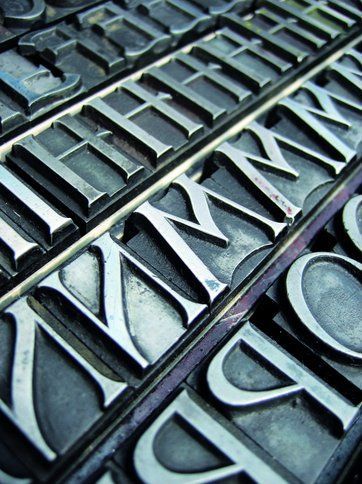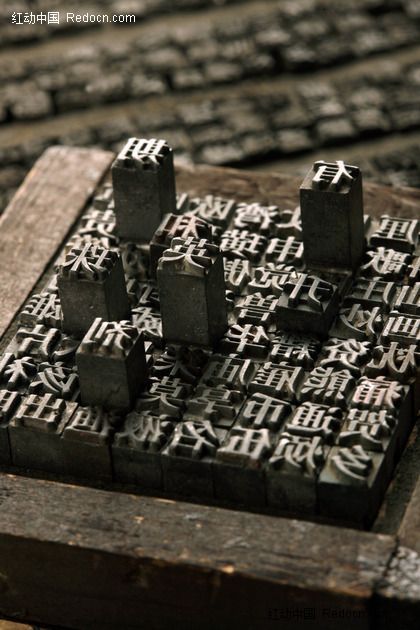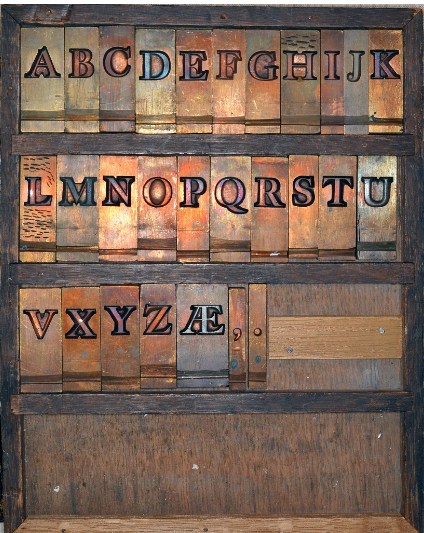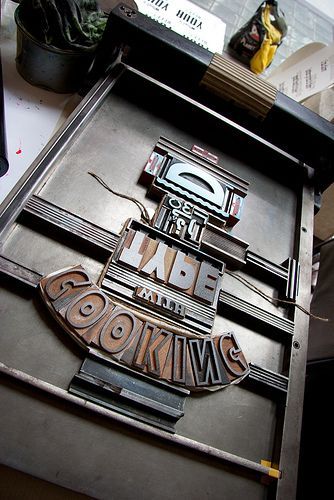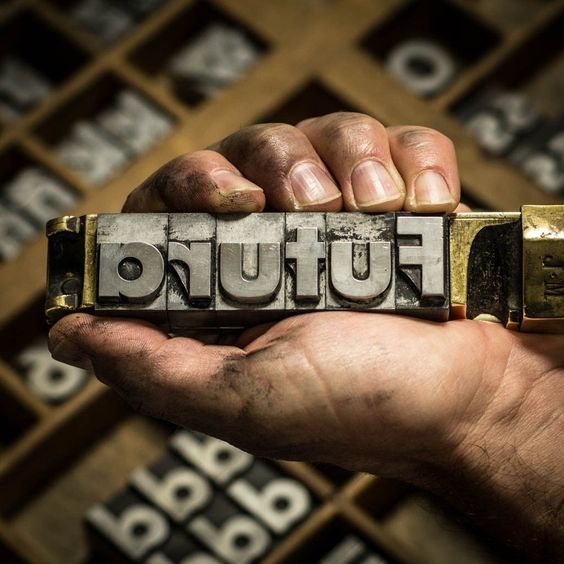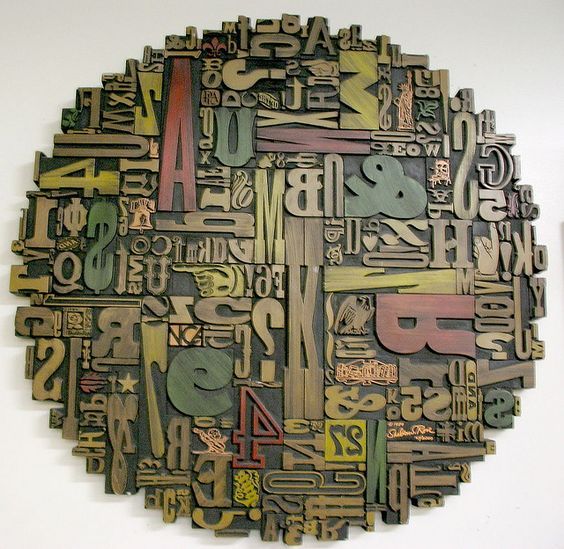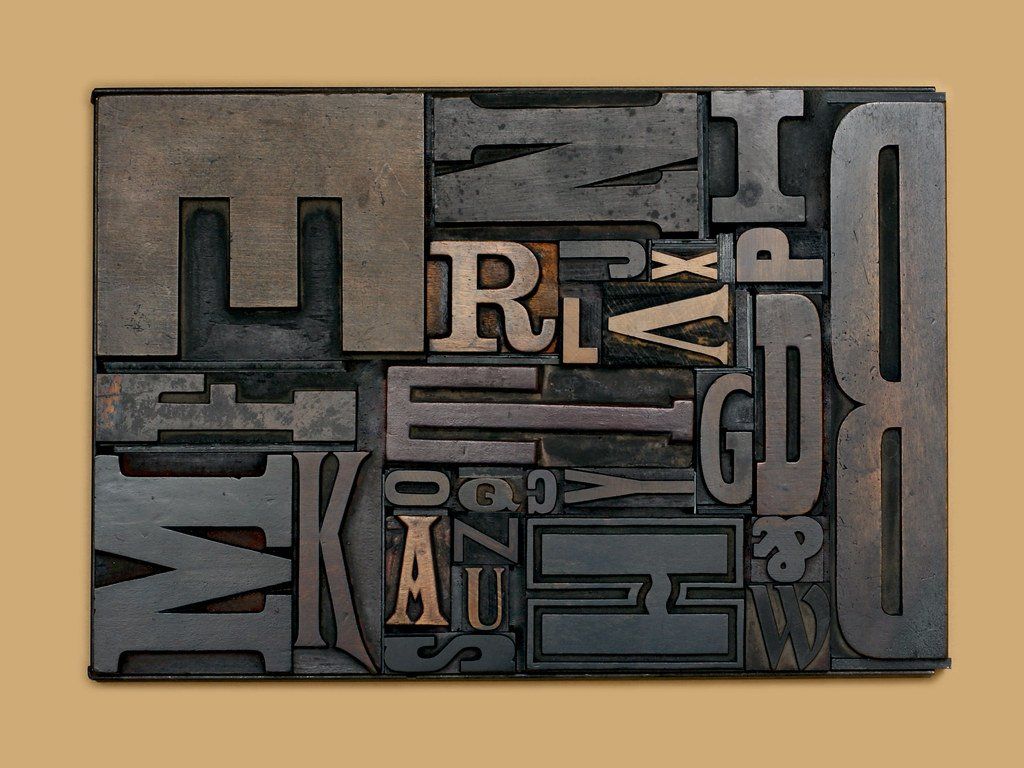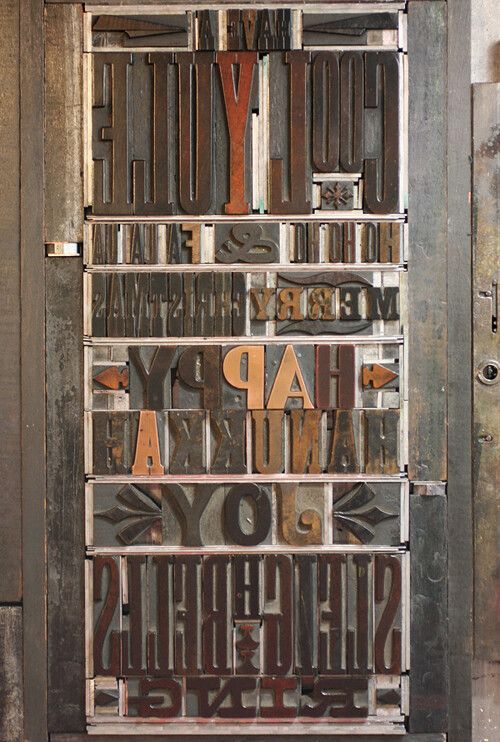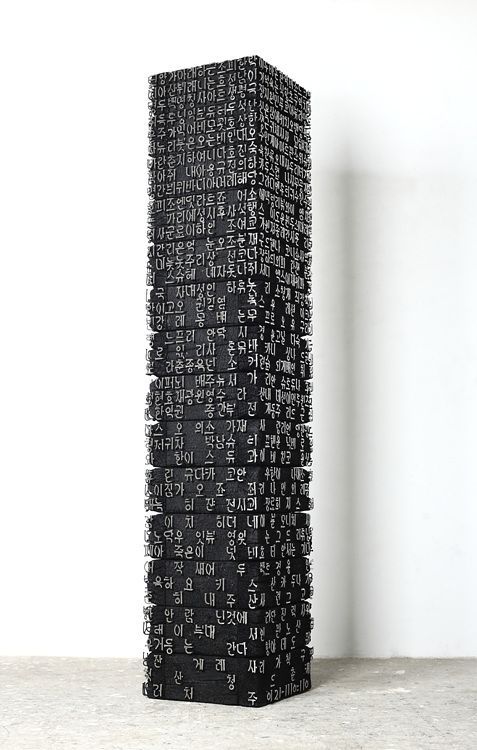
Se conmemora este trascendental inicio del Milenio de lo que será, unos quinientos años más tarde, la imprenta tradicional como el soporte del conocimiento y la cultura en occidente durante más de otros cinco siglos. Así, a partir de la conmemoración de los 8 Siglos de la creación de los Tipos Móviles de Madera, asistiremos a una cuenta atrás en la conmemoración del Milenario de los Tipos Móviles o Técnica de la Tipografía. el año de los primeros tipos móviles fluctúa entre unos 20 o 25 años a partir de ahora. Ello permite comenzar la celebración del Milenio, en este momento en que se cumplen los 8 Siglos de los Tipos Móviles de Madera, y desarrollar un programa de investigación, estudio y revalorización material y estética de estas valiosas piezas de nuestro patrimonio. Ahora es el momento de iniciar una cuenta atrás hasta el último año en que se considera el inicio de los tipos móviles. Un momento en que aún se encontrarán en activo quienes hemos trabajado con esta técnica tipográfica y podemos transmitir, aún directamente, sus valores y conocimiento a las nuevas generaciones digitales.
Piezas, conjuntos o composiciones de piezas, con un atractivo especial y que no son obras de arte de modo expreso. A partir de las piezas reunidas por el titular de esta web se invita a quienes cuenten con piezas de tipos móviles –de madera o cualquier tipo de aleación metálica–.
Además de las obras de la colección Tipometrías, esta sección expone una selección de obras de otros autores, algunas sin intención artística pero cuyo resultado es muy cercano a esta categoría. Se incluyen tipos móviles expresamente y obras impresas con ellos, en lo que se considera técnica tipográfica, desde su reinvención por Gutenberg a mediados del siglo XV, y el fin de su desarrollo en la imprenta tradicional, para transformarse comercialmente en los procedimientos digitales.
En segundo lugar, se ha seleccionado una relación de publicaciones referentes a los tipos móviles, la técnica de la tipografía, y la imprenta tradicional. Como en el resto de secciones, se invita a quienes deseen aportar cualquier información o reproducción, que será revisada y se publicará con los datos correspondientes. En tercer orden se incluye aquí una relación de sitios web relacionados con los tipos móviles, tipografía e imprenta tradicional.